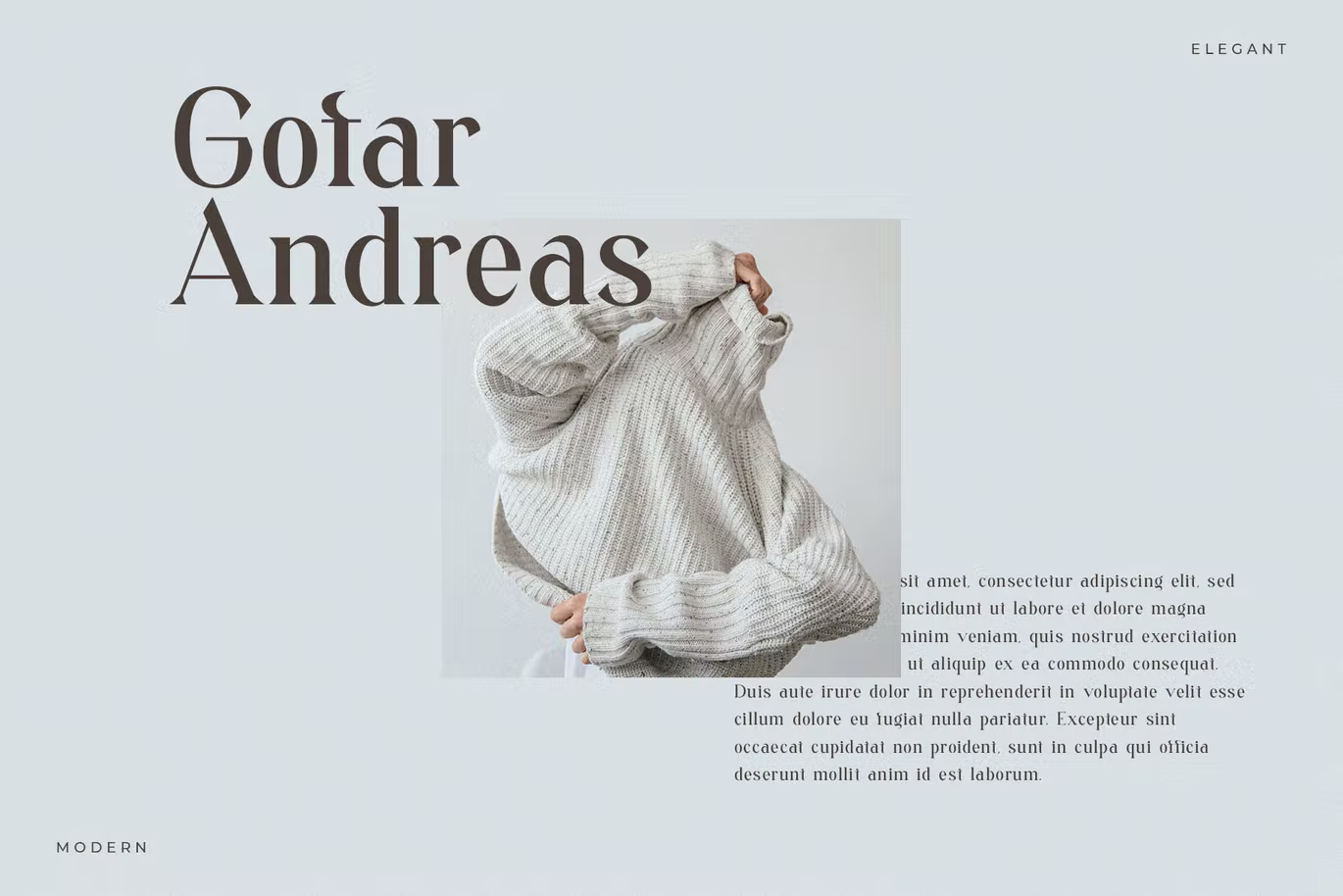
Dusther Font
Description de Dusther Font
Dusther Font est une police de caractères moderne et élégante, idéale pour afficher les titres, les logos, l’image de marque, les magazines, les emballages de produits et les invitations. Dusther est doté de lignes épurées et de courbes douces qui donnent à tout projet une touche supplémentaire de classe.